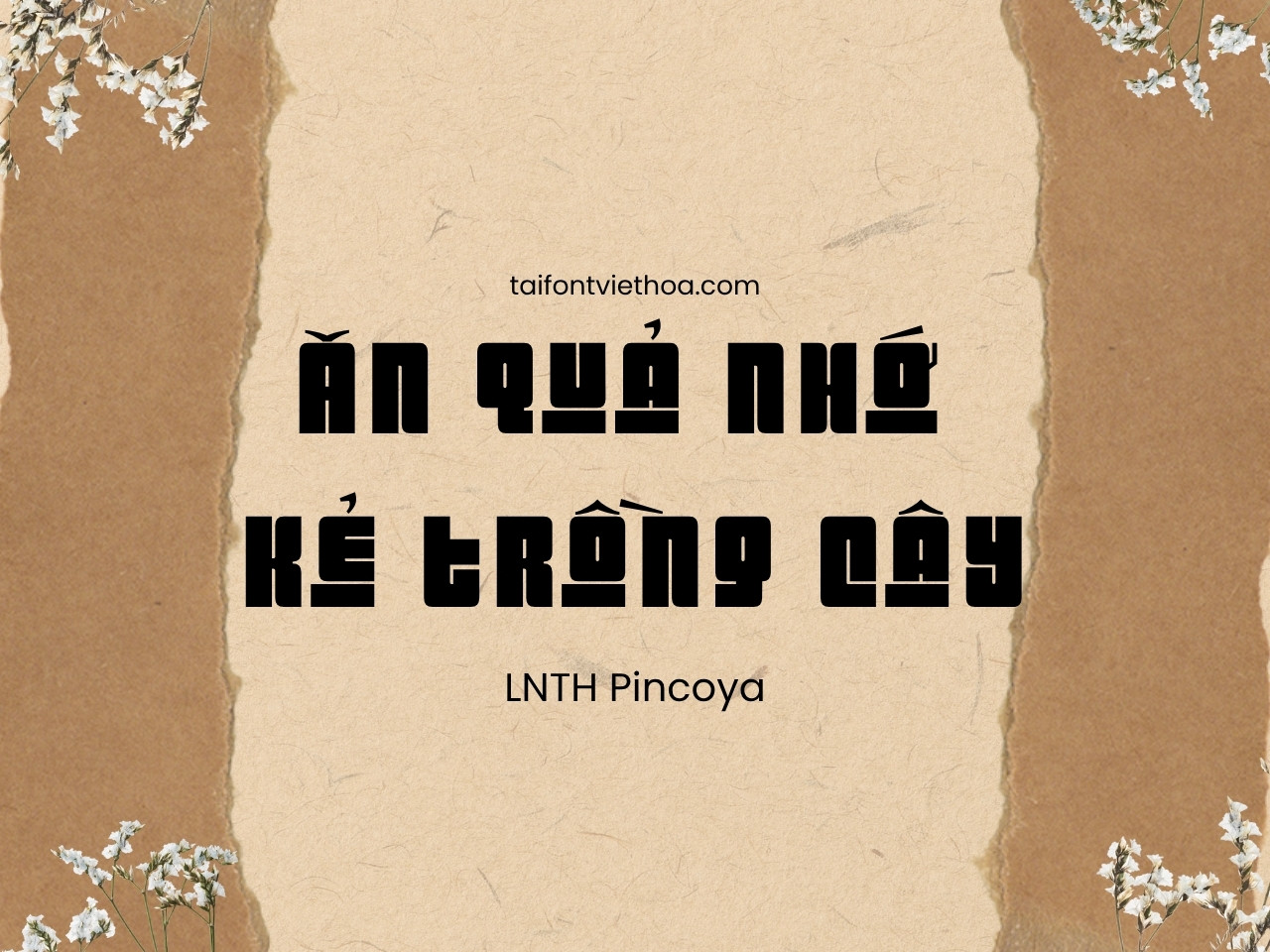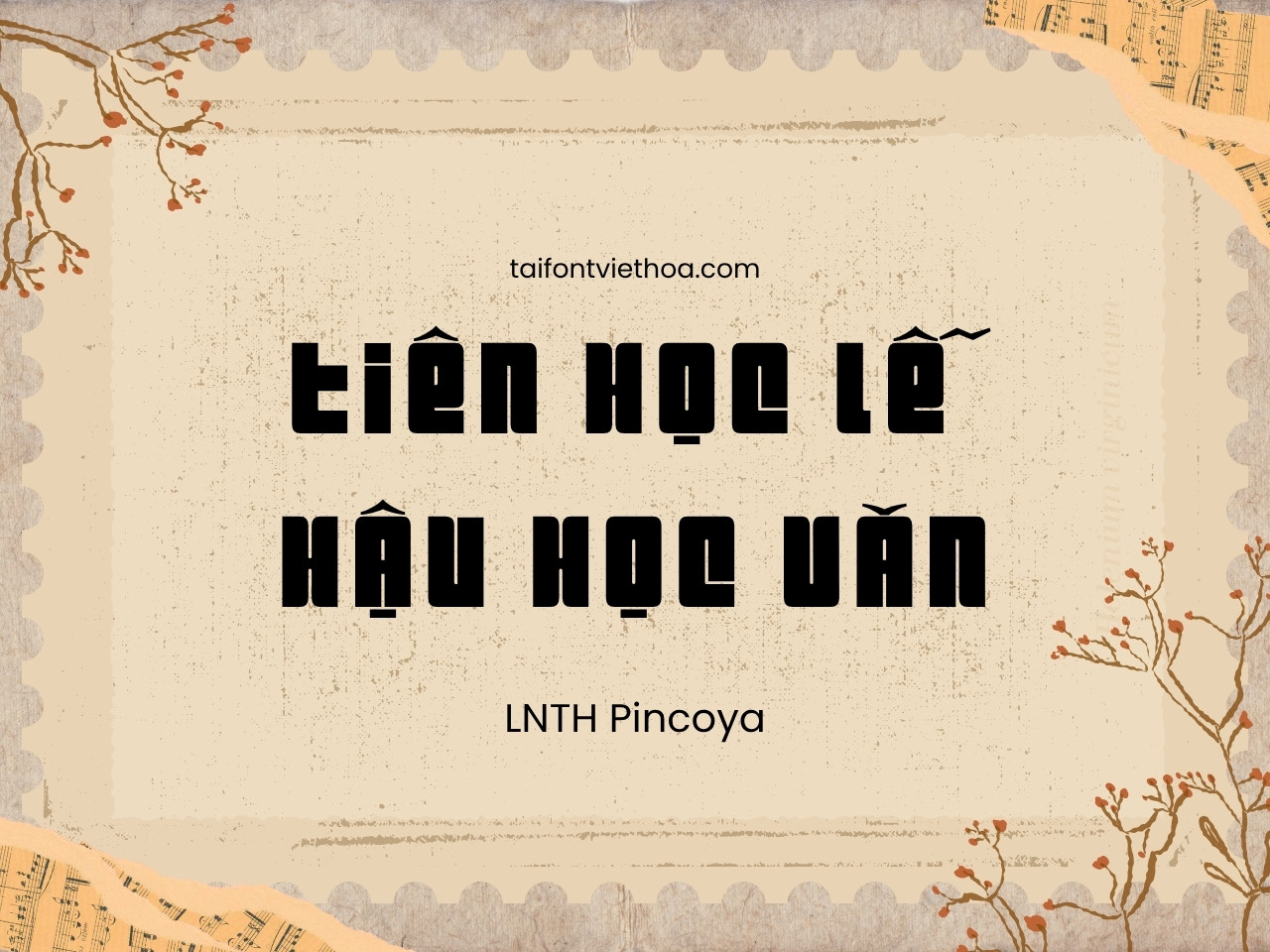
Font việt hóa LNTH Pincoya Black
Giới thiệu về font LNTH Pincoya Black – Font chữ đậm chất hình khối, hiện đại và cá tính
LNTH Pincoya Black là phiên bản Việt hóa từ font “Pincoya Black” do Rodrigo Fuenzalida thiết kế. Đây là một kiểu chữ sans-serif dạng display, mang phong cách hình khối mạnh mẽ với những đường nét to bản, được tạo ra để làm tiêu đề nổi bật và truyền tải thông điệp rõ ràng. Tuỳn Pucca đã thực hiện Việt hóa toàn bộ bộ font này, hỗ trợ tiếng Việt đầy đủ cùng hơn 60 ngôn ngữ khác, giúp mở rộng ứng dụng trên nhiều nền tảng thiết kế quốc tế.
Font được taifontviethoa.com sưu tầm và đưa vào bộ sưu tập các kiểu chữ mạnh, rõ ràng, phù hợp với các thiết kế hiện đại, công nghệ và thương hiệu cá tính. LNTH Pincoya Black mang đến khả năng trình bày ấn tượng, đặc biệt khi sử dụng trong thiết kế đồ họa, biển quảng cáo hoặc poster có sức hút thị giác lớn.
Đặc điểm thiết kế và ứng dụng nổi bật của LNTH Pincoya Black
LNTH Pincoya Black thuộc nhóm sans-serif với các nét chữ vuông vức, dày dặn, tạo cảm giác chắc chắn và có chiều sâu. Thiết kế chữ không có chân, tối giản và sử dụng độ đậm cao, giúp văn bản nổi bật rõ rệt trong không gian hiện đại. Đây là font lý tưởng cho tiêu đề lớn, logo, slogan, hoặc các cụm từ cần tạo điểm nhấn mạnh.
Font phù hợp cho các ngành nghề như bất động sản, công nghệ, tài chính, thương hiệu cá nhân hoặc startup cần sự dứt khoát. Ứng dụng thực tế gồm: thiết kế logo mạnh mẽ, tiêu đề website, giao diện app fintech, poster quảng cáo sản phẩm công nghệ, bộ nhận diện cho doanh nghiệp hoặc sự kiện hiện đại.